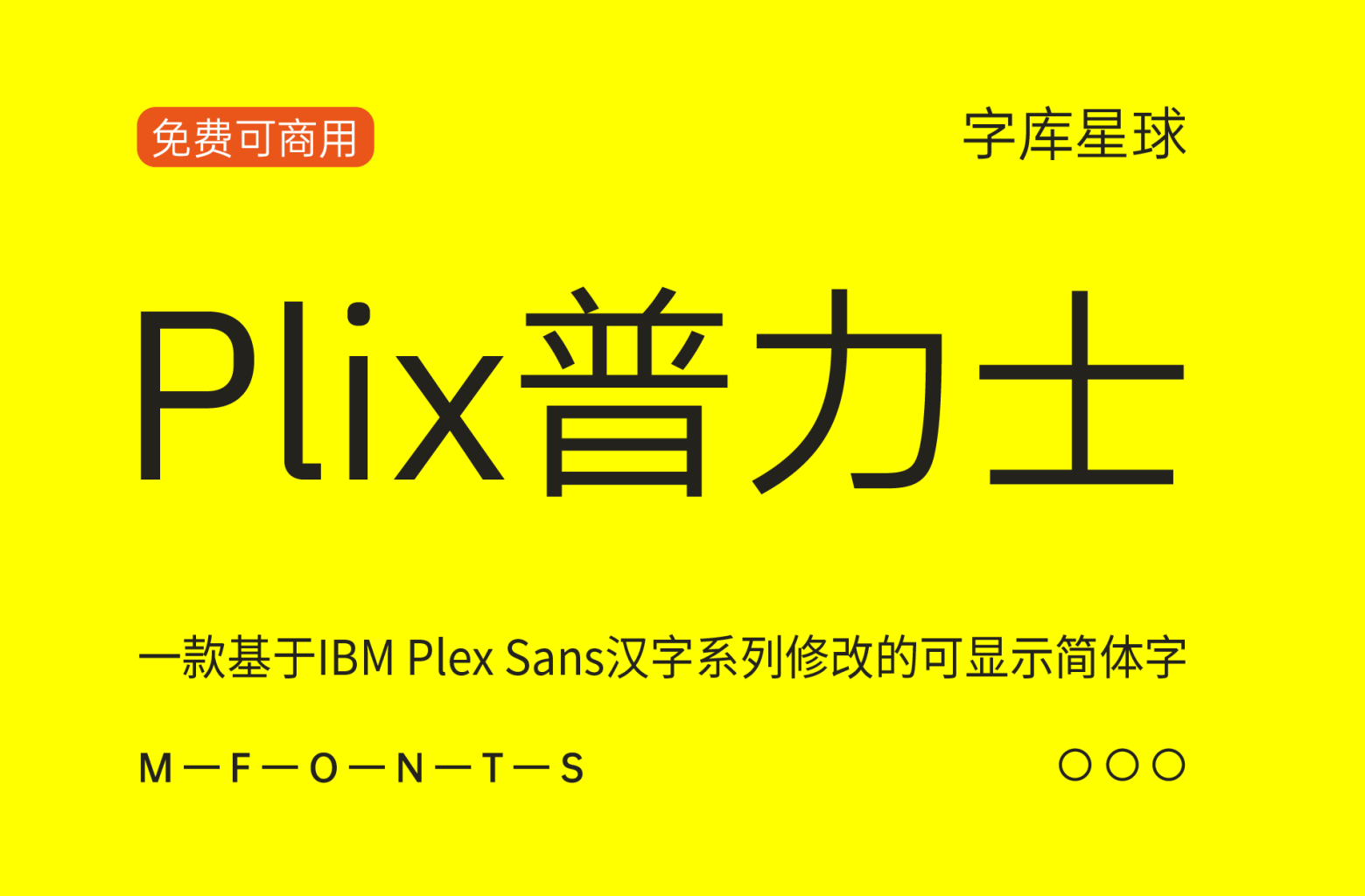
Plix普力士
Plix普力士・潮流黑体|免费商用|人文风mix机械感
Plix普力士是一款基于IBM Plex Sans汉字系列修改,可显示简体字。 下载链接内新增了标点居中版本的Blix,底部也有排版样张。
适用场景关键词:现代、科幻、未来、电子、潮流艺术
Plix普力士:用JP补上TC,再补上SC。标点居角,日本字形
Blix卜力士:用TC补上JP,再补上SC。标点居中,繁中字形